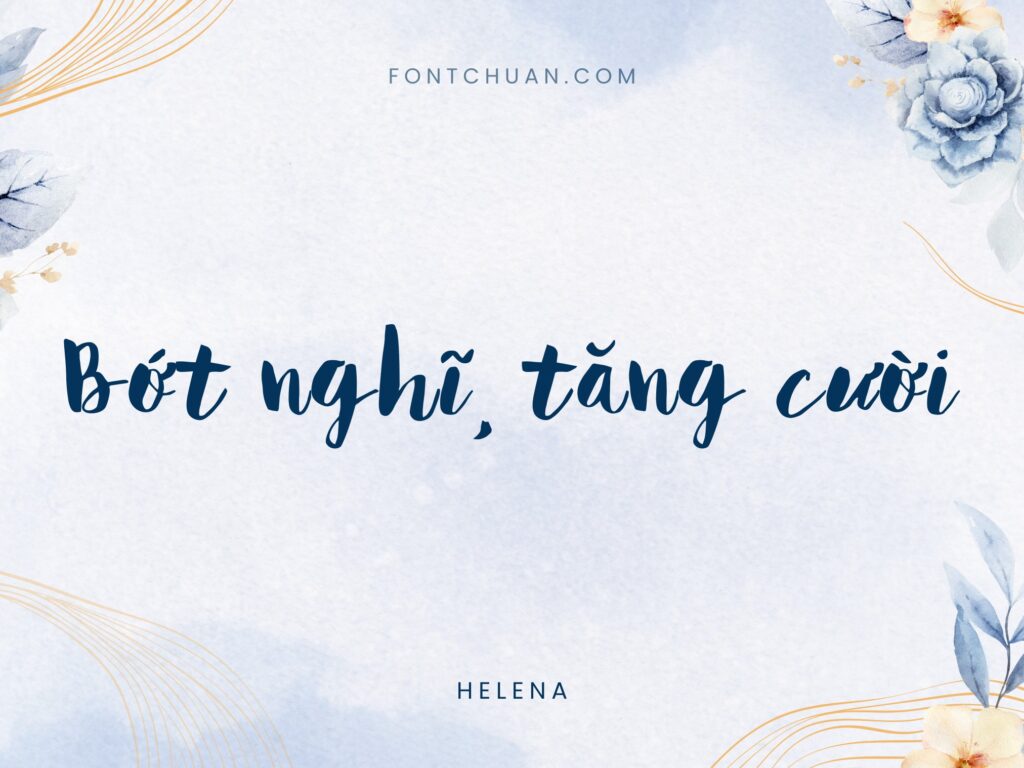
Font iCiel Helena Việt Hóa
Helena là một kiểu chữ viết tay tinh tế được thiết kế bởi Noe Araujo. Font này mang đến cảm giác thủ công chân thực, hoàn hảo cho các thiết kế như logo, thiệp mời đám cưới, phong bì, poster và nhiều ứng dụng khác. Đặc biệt, Helena đã được Việt hóa bởi Iciel, hỗ trợ tiếng Việt cùng nhiều ngôn ngữ khác, đáp ứng nhu cầu đa dạng của người dùng. Thành viên của Font Chuẩn đã sưu tầm và chia sẻ font này, giúp cộng đồng thiết kế ứng dụng dễ dàng trong các dự án của mình.
Về đặc điểm thiết kế, Helena sở hữu các đường nét mềm mại và uyển chuyển, tạo nên sự thanh lịch và gần gũi. Font này phù hợp cho các thiết kế như logo, thiệp mời, bao bì sản phẩm và các ấn phẩm truyền thông xã hội. Ngoài ra, Helena còn thích hợp cho các ngành nghề như quảng cáo, ẩm thực, thiệp cưới và spa, cùng các sự kiện đặc biệt như lễ hội, sinh nhật, Valentine và Trung thu.